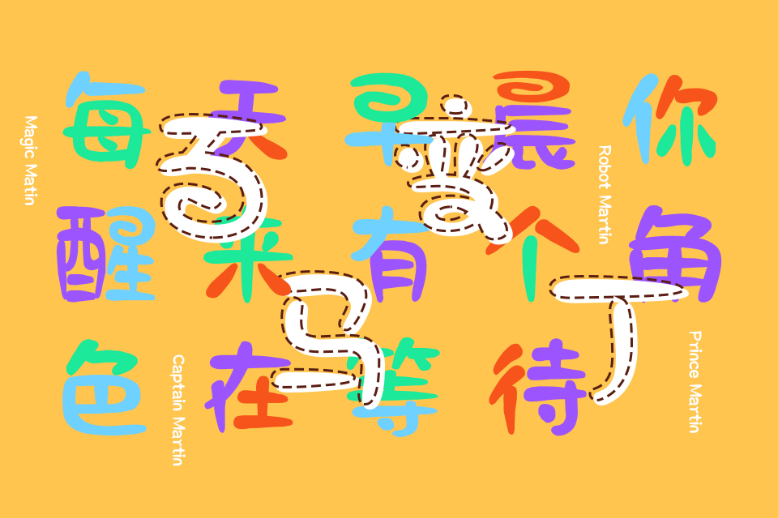
IP定制字体
印品字库针对动画人物马丁的多变形象,与今日动画合作推出一款《百变马丁》字体,这是印品字库的第一款IP字体,旨在通过文字的形式,表现马丁的形象特征,通过个性化的字形设计,让用户在日常使用字体的过程中感受马丁的奇幻冒险与乐观心态。 百变马丁字体的诞生,是印品字库在动画IP领域发展的第一步,具有重要的意义。
开源公益字体
除了为公司企业服务,字体视界在探索更多的字体定制可能性。 “字体视界法棍体”是由字体视界推出的首款免费字体,它将免费开放商业授权给到所有个人和商家,让所有用户可以免费使用,这款字体适用于影视,标题,广告等多种商业场景。
个人合作字体
为书法家、设计师、字体爱好者等制作字库产品,使您的作品永久保留、传播、被使用。